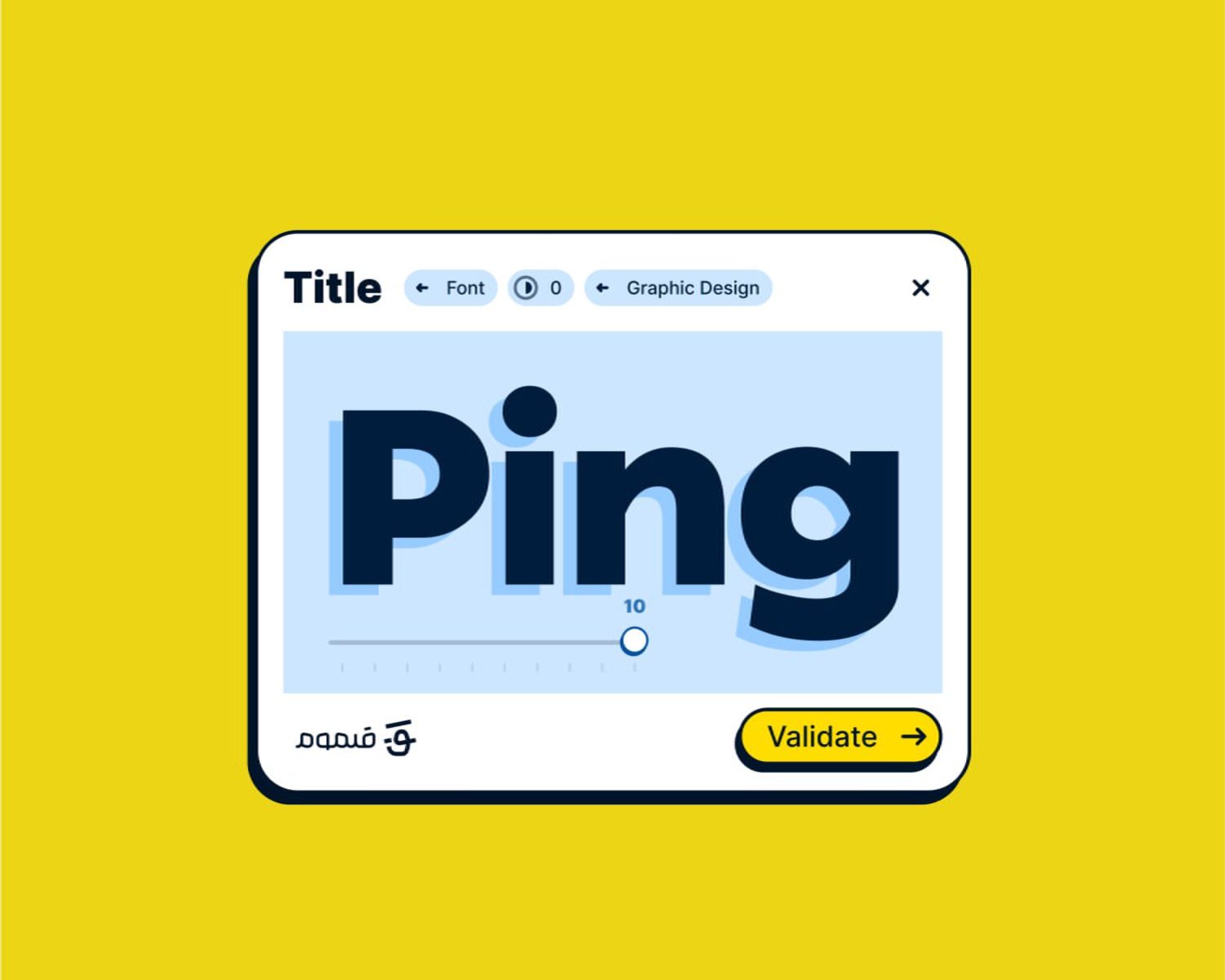
#معرفی خانواده فونت Ping
پینگ یک فونت سیال sans serif با ساختار هندسی است، اما برخلاف دیگر حروف‌های هندسی، Ping تأثیر دست انسان را رد نمی‌کند. حروف ساده شده پینگ با کمترین تعداد ضربه های قلم ساخته می شوند. به عنوان مثال، حروف کوچک «a»، «d»، «p»، «b» و «g» بدون بلند کردن قلم رسم می‌شوند. پینگ قاطعانه مدرن، منطقی اما بدون چهره نیست، پر از احترام به گذشته در حالی که امکانات لحظه حال را بررسی می کند. برای مطالعه مقاله در خصوص پیشینه طراحی فونت پینگ اینجا کلیک کنید.
#یک تایپ فیس برای تمامی زبان‌ها
پینگ فونتی است که از ۱۴ زبان دنیا پشتیبانی میکند و به همین دلیل شما را از نصب هر فونتی بی نیاز میکند. در صورتی که بدنبال فونتی هستید که بتواند مقالات شما را در زبان‌های نوشتاری مختلف پوشش دهد، فونت پینگ انتخاب مناسبی برای شما است
#طراحی بهینه شده فرم‌ها
فونت پینگ دارای یک ارتفاع x فرضی است که با ارتفاع بزرگترین حروف مانند H مطابقت دارد. این ویژگی جایگزینی OpenType یونی‌کیس به این گونه است که حروف بزرگ و حروف کوچک را با هم ترکیب کرده و ترکیبی جدید و سیال از شکل حروف ایجاد می‌کند که فضای بین خط پایه و ارتفاع x را اشغال می‌کند.